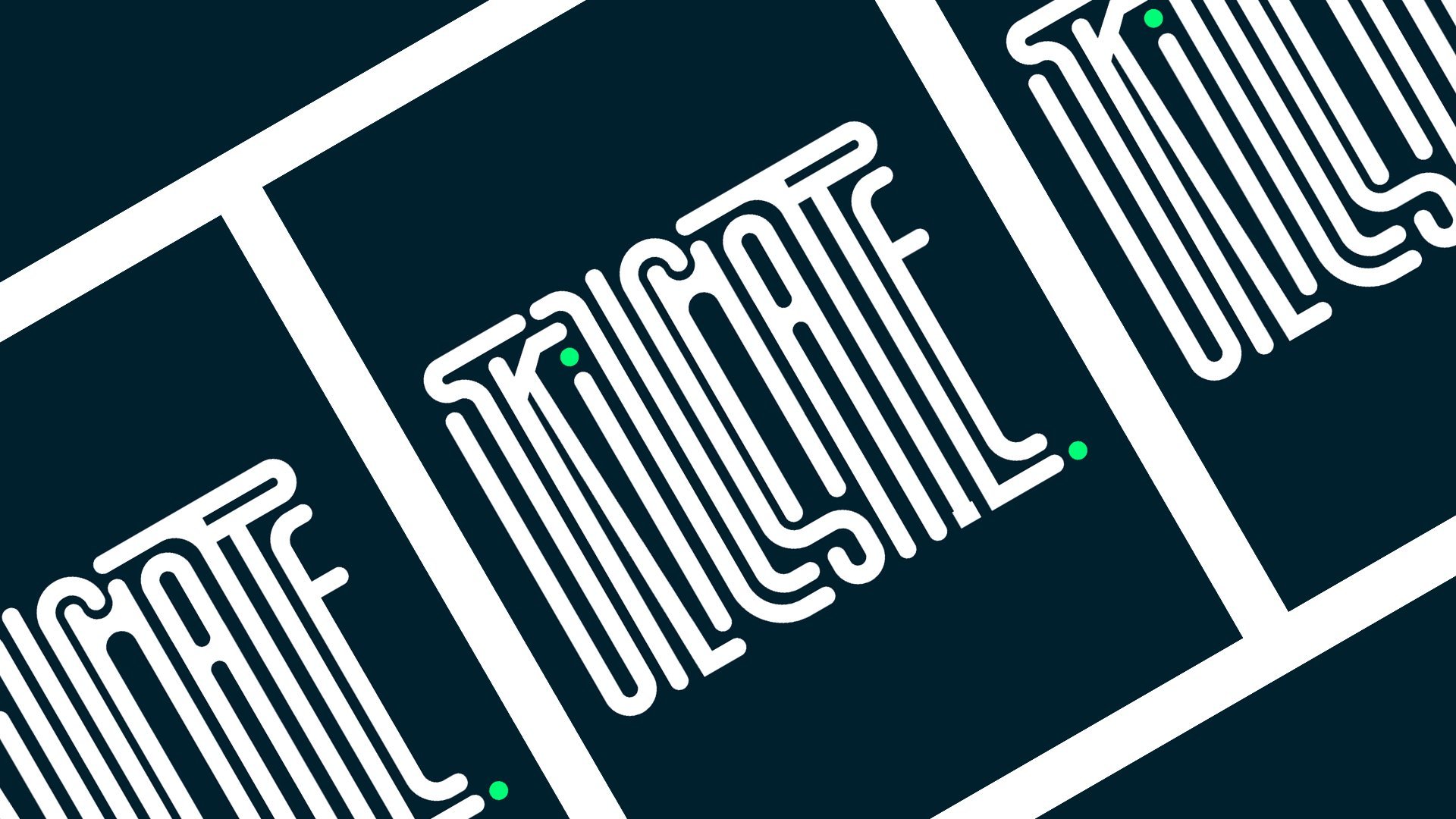
Classe de typographie expérimentale | Marcos Silva | Skillshare
Classe de typographie expérimentale
Leçon 01 Personnalisation de type Partie 01
Leçon 02 Personnalisation de type Partie 02
Leçon 03 Personnalisation de type Partie 03
Leçon 04 Déformateurs de personnalisation de type
Leçon 05 Personnalisation de type Effets 3D
Leçon 06 Ajouter de la couleur à notre type personnalisé
À propos de ce cours
L'expérience de typographie est l'une des choses les plus amusantes et les plus difficiles à faire dans le design. J'adore le processus de création de quelque chose que je peux penser, c'est cool ! Et je peux aussi le lire !
Cette classe s'est inspirée d'un moment où j'ai juste décidé de pousser certains vecteurs autour d'une police de caractères et j'ai fini par faire dire que mon collège de mon côté est vraiment cool. Vous devriez faire plus ! Donc j'ai fait plus et j'ai fait un cours à ce sujet !
Dans ce cours, je vous guiderai à l'intérieur des outils d'illustrateurs adobe bien que vous soyez libre de choisir le chemin que vous voulez si votre résultat est différent du mien c'est ok !
Cette Clas est une expérience, il n'y a pas de client, pas de date limite, personne ne dit que vous ne pouvez pas le faire ou que vous ne pouvez pas en typographie.
Ensemble, nous allons changer de police de caractère, nous allons déformer une police de caractère, la mettre à l'échelle et l'étirer, nous ferons tout ce que nous ressentons.
Je vous assure que vous aurez quelque chose à montrer à votre mère et peut-être qu'elle l'aimera ou non ! Peut-être qu'elle va penser, ce que j'ai fait ? Peu importe que ce soit que nous avons fait quelque chose aujourd'hui !
Ce cours est adapté à n'importe quel niveau de compétence, il est facile à suivre, donc vous n'avez pas besoin de vous soucier de ne pas avoir beaucoup d'expérience dans Illustrator.
Je suis fini ! Alors faisons le maintenant ?
1. Bande-annonce: typographie est autour de nous partout où nous allons et regardons, est la communication. C' est l'interaction, c'est la personnalité et l'expression. Ça fait partie de notre existence. Bien qu'il se sent plus que cela est également matière première que vous pouvez utiliser comme base pour construire et créer des dommages. Cette classe est sur le fait de faire ça. Il s'agit de rendre Type plus expérimental, plus unique et plus personnel. Il s'agit d'obtenir une police de caractères et de la transformer, déformer, de la déplacer, de la mettre à l'échelle de haut en bas. Il s'agit de créer quelque chose de nouveau et d'intéressant avec le matériel qui existe déjà. Bonjour, je m'appelle Michael Silver, designer et animateur, et bienvenue dans mon nouveau verre de typographie expérimentale. Dans cette classe vous guidera dans mon processus créatif et expérimental au sein d'Adobe Illustrator. Nous allons faire la police de caractères et tout changer à ce sujet. Ensuite, nous explorerons les couleurs, les distorsions de distorsion, les effets 3D et les textures. Mais le plus important, nous aurons beaucoup de plaisir à le faire. À la fin de la classe, vous aurez un type personnalisé conçu totalement unique à vous et à votre personnalité, prêt à ajouter à votre portfolio et à partager sur vos pages de médias sociaux. Rejoignez-moi pour créer quelque chose de nouveau aujourd'hui. Alors commençons. 2. Personnalisation de type 01 - Partie 01: Donc, nous sommes un nouveau hétéroclite. Et la première chose que nous allons devoir faire est bien sûr de créer un nouveau tableau d'art. Donc, nous allons d'abord créer un nouveau fichier. Créons de nouveaux, et utilisons dix cents, dix cents pixels. En fait, vous n'avez pas besoin de vous inquiéter pour cette résolution parce que c'est le début. Nous allons juste essayer quelques expériences comme jouer avec le type et frapper réellement exporter notre projet final, que nous exporterons plus tard. Et plus tard, nous pouvons nous inquiéter de la résolution que nous allons utiliser remplissage. Donnons simplement un nom à cette expérience de topographie 01. Appuyez sur Créer, et allons-y. Donc, la première chose est que vous devez en fait, vous pouvez réellement utiliser n'importe quel téléphone pour faire cet exercice. J' ai en fait trouvé ce type dans le site, le font.com, et j'aime vraiment l'utiliser pour ce genre de choses parce que c'est comme une police serif. Et nous ne pouvons pas pousser un peu ces serifs et jouer avec eux, mais vous pouvez en fait utiliser n'importe quelle police de votre choix. Donc, pour cet exercice, j'ai utilisé le nom Skillshare comme plate-forme. Nous allons juste sélectionner cette Skillshare linéaire et juste aller Maintenant, vous pouvez être centré est aligné au centre pour l'instant. Pas de marais Cleveland et prends mon téléphone. Quadro, audacieux. C. Comme vous pouvez le voir, c'est comme non, comme ces équipes de baseball en Amérique, ils ont ce genre de téléphones gras comme vraiment épais. Et nous aimerions sérieux, nous aimerions vraiment de beaux détails. Ce n'est pas comme s'ils étaient à la limite de quoi que ce soit. Je pense juste qu'ils ont le goût d'un très bon début pour quelque chose de même génial. Alors c'est tout. Vous pouvez, mais encore une fois, vous pouvez réellement utiliser n'importe quelle police. Tu veux ? Je pense que celui-ci est en fait plus facile, sont en fait, nous allons le laisser sur les téléchargements pour le fichier dans les téléchargements de fichiers. Donc vous pouvez les gars, donc vous pouvez tous l'obtenir et utilise une police est que j'utilise et peut en fait être plus facile. Et puis vous pouvez simplement expérimenter avec d'autres types de polices, cette même technique. Donc, la première chose que nous devons faire en fait est de sélectionner cette police ici. Et passons à Object and Expand. Allons frapper OK. Ce que cela fait, c'est qu'il élargit notre type. Donc, ce n'est plus modifiable et vous ne pouvez pas le changer. Si vous voulez le modifier, vous pouvez simplement aller à éditer et annuler, développer, puis vous pouvez réellement revenir en arrière et changer le nom si vous le souhaitez. Mais si vous êtes d'accord avec le mot que vous choisissez, c'est bon ? Allons nous agrandir à nouveau. Appuyez sur OK. Et nous allons juste zoomer. Donc, la première chose que vous devez faire est de comprendre comment, comment vous voulez réellement déformer cela. Sur ce cas, je vais juste tirer ça comme je vais commencer par la première lettre S ici. Et je vais utiliser cette touche fléchée ici, l'outil de sélection directe. Vous pouvez simplement aller sur une barre d'outils ici ou simplement appuyer sur a ou v, qui va réellement choisir entre celui-ci. Celui-ci est un outil de sélection qui déplace votre sélection. Il n'édite pas réellement nos nouveaux points moins nombreux. Et celui-ci ici, le blanc, peut réellement sélectionner des points spécifiques et les déplacer. Revenons donc à celui-ci, à la sélection directe, une grande sélection. Et je peux sélectionner les points ou moins comme ça. Donc, comme vous pouvez le voir, tous ces points au-dessus de cette ligne ici sont en cours de sélection. Et je vais les sortir comme ça. Donc nous comme juste un début, c'est déjà à l'air vraiment agréable. Je pense que la police aide beaucoup, bien sûr, parce que c'est comme si c'était un tel héritage. Cette police demande en fait d'être modifiée ou jouée avec. Donc Anchiornis continuent à pousser certains éléments comme ici et jouer avec ça. En fait, expérimentez autant que vous le pouvez. Peut-être que je vais le faire ici. Et si vous n'êtes pas satisfait de ça maintenant, on pourra le changer plus tard. Il n'y a pas ce n'est pas comme si tu étais coincé avec ça pour toujours. Et je vais le pousser un peu vers le bas. Donc il y a quelque chose qui se passe avec ce k ici. Je pense que je vais juste tirer ce point ici pour trouver, peut-être que j'aurai mes guides ici. Je vais voir les règles et montrer les règles. Et je vais tirer un guide du côté. Si vous sélectionnez simplement le guide ici, vous voyez cette ligne pointillée. Et vous pouvez simplement tirer le guide et déplacer simplement le zoom avant en appuyant sur C et simplement sur Z pour zoomer arrière. Juste pour que nous puissions aligner ce point que nous avons passé à la même ligne, points F, juste comme ça. Donc la prochaine chose est juste de continuer à pousser ce K un peu vers le bas. Et je vais continuer à jouer avec les serifs ici. C' est pourquoi j'aime vraiment utiliser cette police pour cet exercice. Ces serifs sont en fait fonctionne si bien et ils en fait si facile à éditer. Mais encore une fois, vous pouvez réellement utiliser n'importe quelle police. Et faites comme ça. Peut-être qu'on les gardera. J' aime ça. En fait, je vais tirer ces haut, le haut de la lettre I Morales ici. Parce que ce que je veux faire plus tard, Il est également ajouter de nouveaux éléments à cela. Vous pouvez donc modifier votre police de caractères. Et, et avait en fait quelques détails à elle. Et je vais tirer, peut-être que je vais pousser encore un peu plus. Alors je peux tirer un peu plus la lettre S, juste comme ça. Et peut-être que je vais le faire. Alors je peux étendre la jambe du k sous cela. Et continuant à créer ce genre de puzzle que vous avez tort, comme travailler, désolé, je ne pouvais pas me souvenir du nom en anglais. Et vous obtenez les lettres impliquées les unes avec les autres en créant ce genre de compositions presque complexes que la Russie devra prêter une certaine attention pour réellement comprendre et lire. Et c'est ce que je trouve vraiment intéressant. C' est comme quand vous en fait, il n'y a pas, il y a quelque chose là-bas. Eh bien, en fait, vous devez faire attention et le lire du tout, comprendre ce qui se passe là-bas. J' y arriverai rapidement plus tard. Et peut-être que je vais changer cette lettre L aussi. En fait, j'ai oublié de faire quelque chose qui est que je dois dégrouper cette lettre. Sinon EBIT, si je le déplace, je peux déplacer des individuels si j'en ai besoin. Donc, juste pour sélectionner en utilisant notre outil de sélection ici. Et je vais à Object and Ungroup. Parfait. Et maintenant, nous allons éditer ma lettre L. Je vais la tirer vers le haut. Et ça va pousser ça un peu comme ça. Et nous allons MOOC oh, deuxième moi de retour. Ainsi, ils peuvent tourner les uns avec les autres plus ou moins comme ça. Et en tirant. Encore une fois, l'idée ici est de créer comme, comme la composition plus agréable que vous pouvez. Peut-être qu'en fait il suffit de tirer ça. C' est le réel dépendra du type que vous utilisez. Donc je suis vraiment curieux de savoir quel mot avez-vous entré que nous utilisons pour cet exercice ? Parce que c'est un monde différent. Nous avons en fait une composition différente. Et c'est là qu'il le ferait, ce qui le rend si intéressant et si unique. C' est comme si un, si les gens utilisent le même mot, ils auront une approche différente de cet exercice. Et nous serons vraiment intéressés de voir comment vous utilisez réellement les contrats du même mot d'une manière différente. Et je ne sais pas si tu sais ce que je veux dire. Comme si c'était parce que c'était très personnel et que tu avais ton type de personnalité à elle. Peut-être que je vais le faire comme ça. Et puis on poussera ce H ici. Je vais, encore une fois en utilisant l'outil de sélection ici, je vais tirer cela vers le bas. Je suis désolé, j'utilise probablement toujours le raccourci, ce qui est une envie. Parfois, je ne vais pas à la barre d'outils et j'appuie juste sur un et je continue juste. Je suis désolé si cela vous dérange, mais vous pouvez en fait utiliser aussi bien, ce qui est un très, vraiment sympa un raccourci clavier pour l'utiliser. Et vous en fait simple petit peu de temps. Je n'entends pas tout le temps là-bas. Choisissons simplement ceci. Et je suis quand j'ai besoin de sélectionner deux points différents. Mais je peux le faire en une seule fois. J' utilise réellement le maintien, la touche Maj comme ceci et je les sélectionne. Donc, le clip sélectionné, puis je déplace cela vers le bas. Voyons voir. Quand je déplace celui-ci aussi ici. Nous allons pousser un autre guide ici pour nous assurer que le H correspond réellement au k là. Vous n'avez pas besoin de réellement vous pouvez libérer comme vous le souhaitez, n'avez pas besoin d'utiliser les grades Kaiser. C' est, c'est expérimental, alors soyez libre de ne pas suivre n'importe quel type de règles et juste s'amuser. Et je suis, je fais ça pendant un moment. En fait, j'aime parfois qu'il garde une sorte d'ordre parce que ces compétitions sont si complexes d'une certaine façon. Je vais juste garder, donc parfois je vais juste zoomer avant et arrière pour que je puisse vraiment voir plus ou moins comment, comment ça va couvrir ? Comme, je pense que si vous faites un zoom arrière, ça peut avoir une meilleure idée de ce qui se passe. Et quand vous zoomez, vous savez si bien ce qui se passe dans la composition ? C' est pour ça que je fais toujours ça. Je suis désolé. Et déplaçons juste la lettre a ici. Donc, comme nous avons le H là-bas, je pense en fait pousser cette page un peu comme ça. Déplacez notre serif du ciel ici et poussez celui-ci vers le bas. Peut-être l'aligner. Encore une fois. Tu n'as pas besoin de voir, supposons que tu t'amuses. Et si vous travaillez avec des notes InDesign, je travaille à temps plein. Parfois, ça devient si traditionnel. Vous pouvez faire beaucoup avec les polices de caractères parce que Donald, ils proviennent d'un client ou de leur police de marque. Et vous êtes un peu limité ce que nous pouvons faire avec eux. Vous devez respecter les règles, donc je ne veux pas créer de règles ici. Je veux juste que tu t'amuses et que tu crées quelque chose de nouveau. Alors faisons ça. Ici. Juste comme ça, peut-être que je vais pousser ça vers le bas. Essayez de gérer ça. Oui, parfait. Comme peut-être que j'essaierai à nouveau demain. Parfois, je éteins mes guides que vous pouvez simplement aller ici à nouveau et juste montrer guide. Donc s'ils ont disparu dans votre écran, je vais juste à Delta. Maintenez à nouveau la touche Maj pour sélectionner plusieurs points. Et juste faire super. Et bien, continuons. Je pense que nous avons tendance à penser que je suis vraiment content de cette sélection. Nous sommes juste maintenant, nous avons le, notre, nos cendres est en fait assez difficile parce que la façon Iz conception réelle, parce qu'il est juste besoin d'un coin supérieur ici. En fait, je dois faire quelque chose comme ça pour ne pas perdre la forme du R et devenir quelque chose d'autre que vous pouvez réellement le comprendre. Pour être très prudent avec celui-ci. Selon un téléphone que vous avez choisi de faire cet exercice où il n'a pas vraiment d'importance parce que peut-être votre r n'est pas aussi bloqué que celui-ci. Et ceux-ci, vous pouvez probablement faire ce que vous voulez. Ne perdez pas les informations qui sont parfaites. Désolé, parfois je prends ces pauses pour boire de l'eau. Et j'ajoute le contraire, quand je l'expliquais avant juste par notre sœur, je sais que faire ça est des cours de Skillshare et je suis tout à fait connu sur l'enregistrement moi-même expliquant quelque chose. Donc, à chaque fois que je fais un cours, j'ai vraiment développé cet ensemble fou. Et je commence à avaler et à respirer très profondément pendant que je suis en train d'enregistrer et je pense que c'est tellement ennuyeux, mais je ne sais pas si ça va être fini, mais je vais continuer parce que j'ai beaucoup aimé ça pour arrêter. Et d'accord. Donc, comme vous le voyez déjà, je pense qu'on pourrait jouer un peu plus. Qu' est-ce que la lettre E gauche ? Maintenant, tu vas juste tirer ça comme ça. Oui. Et oui, je pense qu'on a déjà une très belle composition qui se passe ici. On dirait une empreinte numérique, comme une empreinte digitale. Et réel, réel comme il voulait vraiment faire quelque chose ici sur le, J'index quelque chose de plus proche de la, à la police de caractères. Donc, donc chacun a en fait un peu d'influence comme une étiquette de couleur graffiti sur elle. Je ne sais pas comment. Je commence juste quand j'ai commencé à faire ce genre de travail. Nous tapons des visages. Moi, je viens de commencer à modifier certaines phrases temporelles parce qu'en ce moment, je travaillais dans une agence et le travail que je faisais n'était pas, elles sont très créatives. Et je veux juste ouvrir Illustrator et commencer à jouer avec des polices et finir par faire cet effet vraiment cool. Et j'ai continué à le faire pendant un moment. Parfois, nous avons besoin de s'ennuyer pour créer quelque chose de cool. Je pense que l'ennui est comme nous, nous ne respectons pas vraiment. Je pense que l'ennui est aussi important. Continuez à bouger cette chose, essayant de faire des formes différentes. Et vous pouvez en fait continuer cela pendant des siècles, pendant des heures si vous le voulez. est important, c'est que nous sommes sûrs que vous essayez réellement de déplacer des choses et de créer différents types de compositions. Et voyez lequel. Peut-être bouger l'œil, l'a ici. Peut-être que je vais choisir ces points ici. Et je vais le faire descendre. Oui. C'est un peu différent. Peut-être la même ligne que le H ici. Tout comme oui. Eh bien, je pense que nous avons notre première expérience. La première chose est comme, comme vous pouvez le voir, est juste de jouer avec la forme et de la modifier autant que vous le souhaitez. Toi. C'est illimité. n'y a aucun moyen que j'aime le résultat Hendra. Tu es en fait, tu peux y aller. J' étais comme je l'ai dit, on peut juste continuer à le faire et le modifier. Ensuite, je crée un nouveau div, nouvelles formes et je déplace les curseurs autour. Peut-être, bonsoir. Peut-être qu'on va pousser ça. Donc c'est vraiment dur d'arrêter. En fait, si vous, parce que vous obtenez ainsi dedans et essentiellement si divertissant, presque comme juste continuer à modifier ces formes, ces lettres, et créer de nouvelles formes. Ce type de loyer de terrain que nous pourrions réellement mettre quelque chose ici au milieu et poster comme collaborer en ligne et dire, essayer d'entrer dans le point de terminaison ou autre chose, il suffit de supprimer cela. C' est là que j'aime commencer. Je voudrais commencer par quelque chose comme rapide et réellement basique, mais quelque chose de rapide et différent. Et à partir d'ici, le C sera notre première expérience. Distorsion et maintien de la base de la forme continue immobile de la lettre. Désolé. Ensuite, je voudrais modifier encore plus loin d'ici. 3. Leçon 02 de personnalisation - Partie 02: Donc, pour que nous ne perdions pas ce design ici, je vais juste sélectionner l'outil Plan de travail ici sur le coin. Et je vais déplacer ce plan de travail vers la gauche. Et sauvage, je suis sauvage pressant Alt. Je vais juste le tenir et le faire glisser sur le côté. Juste comme ça. Donc tu compliques mon plan de travail. Et ça garde mon design là. Et nous gardons ces plans de travail ici juste pour la sécurité. Et donc si vous avez vraiment besoin de retourner ici, on peut facilement copier ailleurs. Donc celle-là nous, nous avons conçu en premier, c'est très dur bord. n'y a pas de coins très mous ici. Et terminer chaque article est cool. Si vous êtes satisfait de cela, vous pouvez juste arrêter tout de suite et juste aller à la prochaine, la prochaine des formulaires. Et il suffit d'expérimenter avec les couleurs et la 3D. Mais si vous voulez vraiment explorer un peu plus, il y a autre chose que vous pouvez faire sur cette police. Donc, en fait, j'aime aussi continuer à éditer cela. Peut-être que je vais juste nettoyer quelques bords comme ici parce qu'on n'utilise pas celui-là. Donc, quatre qui sont en cours, juste, vous pouvez simplement peut-être supprimer les points de votre outil de stylet et utiliser l'outil Supprimer le point d'ancrage et nettoyer les points comme ceci. Et peut-être porter un guide du coin à nouveau. Et juste moins Tony propres Guides, Show Guides. Et puis aligner les guides comme ça. Ou vous pouvez vraiment l'utiliser et juste en trouver un dont nous n'avons pas besoin. Tout comme celui-ci ici, où vous pouvez réellement utiliser l'outil de forme, l'outil de rectangle ici. Et c'est sur un rectangle comme ça, correspond parfaitement au coin que vous voulez supprimer et il suffit de sélectionner votre lettre et votre rectangle et d'aller trouver Pathfinder ici. Utilisez simplement ce mode différent, le modèle Minus Front, qui supprimera l'objet qui se trouve devant la lettre. Nous ne ferons pas cela par étape. Donc, certaines mères en auront besoin, un autre avis que nous voulons donc pas bon, pas de souci beaucoup en ce moment. Mais je pense que je voulais faire sur ces lettres pour qu'on fasse ces virages. La façon dont vous voulez le faire est d'utiliser notre outil de sélection. Je vais sélectionner ces deux coins ici. Et je vais pousser ces petits points blancs ici comme ça jusqu'à ce qu'ils fassent un coin rond parfait. Et je vais continuer à faire ça ici. Et sur celui-là. Comme ça. Donc, de cette façon, nous créons un différent que différents troubles comme il est plus arrondi et plus doux et commander un avant. Faisons-le juste. Joli. K lettre aussi. Choisissons cet arc. Peut-être commencer par 1 d'abord et essayer de faire une belle courbe. Et supprimons simplement ces points ici parce que nous n'en avons pas besoin. Et essayez juste de faire la meilleure courbe qu'on puisse entendre. Parfois, ceux-ci sont difficiles parce que vous devez garder la même largeur entre les deux et parfois pas si facile à utiliser. Oui, quelque chose comme ça. Parfait. Donc je vais aller au sommet ici. Je vais tirer ça vers le bas. Celle-ci aussi. En fait, peut-être que je vais commencer par celui-là parce que nous ne voulons pas tuples qui choisissent peut-être ces deux points, celui-ci et celui-ci. Et fais ça. Alors. Et puis on le fait peut-être ici. Et celui-là. Poussez ces deux points ensemble comme ça, et peut-être que celui-ci n'aura pas vraiment. C' est juste parfois assez difficile à faire en fait. Oui, il suffit de le sélectionner à nouveau. Peut-être que je peux juste le faire à la main jusqu'à ce que ça soit beau. Parce qu'on peut faire une forme parfaite comme ça, juste essayer de le faire. Donc, il garde la même largeur ici. Oui. Parfait. Allons éteindre nos guides. Je vais juste voir des guides. Guides pour le moment. Et merci celui-là comme ce coin Rhonda du K. Peut-être voyons si nous pouvons vraiment savoir. Fais juste ce coin. Peut-être, peut-être que je vais juste tirer, continuer à éditer le cygne ici. Donc c'est en fait la ligne droite ici. Et peut-être en fait va tirer ce terme en sélectionnant ici. Et je vais pousser ce K. Je dois partir un peu plus loin. Et peut-être que je vais supprimer ceci ici. Modifiez depuis le début de ma phrase de type. Vous voyez, nous avons déjà défini à partir d'ici parce que ce qui est, parfois ce qui fonctionne sur cette tuile. Ils le feront, ils travailleront vraiment beaucoup sur celui-ci. Et vous continuez à vous améliorer et à vous adapter comme vous le souhaitez. Allons juste tirer ça, faire mal, va toujours le faire rond. Les gars vont avoir cette partie supérieure. Juste comme ça. Et celui-ci en fait, je vais supprimer ces coins en utilisant l'outil de suppression ici. Et supprimez simplement. Je vais utiliser un guide pour m'aider à aligner ces points là. 00 cartes. Donc oui, à la même chose, ce point ici. Je vais supprimer ces points parce que quand je fais réellement la courbure, ces points arrêteront ma carrière là-bas. Et je ferai de même. En bas. Sélectionné. Supprimer les points d'ancrage. Juste comme peut-être que je vais juste cliquer sur celui-là droit. Et puis je vais juste tirer ça en utilisant notre code. Je vais supprimer celui-là. Parfait. Paul est plus court, tout est beau quand je zoom arrière. Faisons tourner nos guides de guides. Il a l'air très beau tableau. Et peut-être que je vais juste sélectionner ceci et le tirer vers le haut. Je vais supprimer celui-là. Can, je vais essayer de le faire suivre la même chose. On en a un carré. Et je vais me tromper. Donc, je correspond vraiment. Et ensuite, nous vous demanderons ce coin ici. Voici la recherche vraiment heureux avec ces résultats déjà. Continuons à pousser. Cela peut être, je vais continuer à éditer ce k. juste quelque chose comme ça. Bricoleur. Nous allons supprimer ces points ainsi sur le L. Allons obtenir toutes les spécifications gentils ici, montrer sortes. Et supprimez simplement ce point. Guide ici. Supprimer ce point est tout à fait un exercice sans fin parce que c'est comme bouquet. Comme je l'ai déjà dit, vous pouvez simplement continuer et continuer à expérimenter que la stabilité style Follies est comme chaque fois que vous modifiez quelque chose que vous obtenez un nouveau IT, et puis vous avez juste une autre idée. Et puis. Vous avez vraiment besoin de vous contrôler, donc ça s'arrêtera même si vous, sinon vous allez être là dedans. On va finir parce que tu vas l'éditer tout le temps. Mais c'est ce qui arrive quand on s'amuse. Vous réparez. Je veux juste continuer à s'amuser et continuer à concevoir des trucs cool. C' est tellement Mode. Vérifie un peu. Oui, en fait, va supprimer celui-ci ici aussi. Je vais chercher un guide ici. Je vais supprimer celui-ci et celui-ci. Poussez ce point vers le bas, faites le mal. Bien sûr, comme il est vraiment difficile d'utiliser ce genre de style dans notre travail quotidien, en fonction de l'industrie pour laquelle vous travaillez. Peut-être qu'elle a travaillé pour Nike ou si vous êtes un designer indépendant ou illustrateur, sera plus facile à appliquer comme ça. Mais je pense que quand je fais réellement ce genre d'exercices créatifs et d'expérience Mike, une certaine façon, je reçois, je développe de nouvelles idées ou compétences que je peux utiliser dans le projet professionnel à mon travail. Ce qui est comme, je ne pourrai jamais modifier notre forme de marque comme ça. Bien que peut-être je peux apprendre quelque chose de la composition et effectivement présenté à mon directeur artistique et peut-être peut nous inspirer à essayer de prendre un peu plus de risques. Mais je n'ai cette procession qu'à cause de petits exercices que je recommande de faire tous les jours. Et c'est vraiment cool parce que comme quand vous faites quelque chose d'expérimental à cela, vous avez en fait la chance de suivre votre voix, suivre vos décisions. Vous savez, pas comme suivre une ligne directrice très spécifique de la marque. n'y a pas de ligne directrice qui avait poumon est d'avoir du plaisir et expérimenter et de partager cela avec le monde et peut-être inspirer quelqu'un. Ou peut-être que vous faites juste une nouvelle affiche pour votre chambre. Tu sais, ce n'est pas comme si je n'avais pas besoin d'attendre quoi que ce soit de ça. Encore une fois, juste s'amuser. C' est pour ça que je fais ce cours pour autant de tests. Tabouret, supprimer est L aussi bien à Marshall vraiment apprécié tant. Et j'ai fait cet exercice plusieurs fois afin que je puisse réellement l'expliquer et essayer de le rendre aussi divertissant que possible. Mais c'est juste comme c'est différent de mes autres tutoriels qui sont plus IE, ils sont plus techniques d'une certaine manière. Et celui-ci est juste, est plus créatif que technique. Et ce qui me donne plus cette occasion d'être réellement dans la conception de ceci et en fait le garder comme ce genre de conversation et d'expliquer quelques morceaux de décisions blanches et pourquoi je fais cela et pourquoi permettre tant d'expérimenter et partager cette vidéo. Peut-être que je vais juste tirer ça un peu ici parce que je pense que cette forme ici est vraiment petite par rapport aux autres. Donc je vais juste pousser ça un peu comme ça ici. Je vais avoir besoin de déplacer ce S va sélectionner ces points parce que lorsque je déplace cette forme de L là-bas, j'ai besoin d'adapter la lettre S aussi bien. Et je vais m'assurer que je fais ce tour aussi. Et maintenant, faisons-le comme ça. Comme ça. Parfait. Oui, j'ai l'air super. Encore une fois, je vais juste supprimer ces points ici parce que en fait ne pas faire beaucoup sera amusant si j'étais en fait, était en quelque sorte mettre le L à l'intérieur. Mais alors j'aurai besoin de peut-être que je peux l'essayer, mais maintenant peut-être que je vais juste partir comme ça. Je vais juste supprimer ces points ici et je vais juste y aller. Parfois, c'est parfois facile. Gardez votre vie simple pour le temps et je ne veux pas que vous partiez de votre journée pour expliquer ça. Donc je montre ce processus. Je vais juste pousser ça ici. Donc, ces guides m'aident beaucoup. À la fin de, comme tous les côtés actifs, je finis avec des médiums de guides. Et si tu bouges ton cœur, pour une raison quelconque, tu en fait, Yochai n'a plus de sens. Et il est si dur, parfois je fais ça. Et je vais juste sélectionner ces points ici. Et celui-là. Je vais juste pousser comme ça, comme ça. Comme si vous essayez de les aligner plus ou moins pour réellement vous aider à garder la même largeur de trait. Et nous ferons la même chose ici. Ce sera encore dur parce qu'on n'a pas beaucoup d'espace pour qu'elle bouge. Est donc peut-être que je vais essayer de changer cela un peu. Laisser S est en fait difficile aussi. Comme nous l'avons vu ici, est à cause de cela, en fait ce contraste de différentes formes. Peut-être que si je pouvais juste avoir plus d'espace là-bas. Je vais pouvoir, euh, vraiment intéressant comment nous envers vous, vous avez décidé d'utiliser un oeil et s'il vous plaît assurez-vous de partager ça parce que ce sera tellement amusant. En fait, deux personnes décident d'utiliser les mêmes mots et ils ont des approches différentes et des concepteurs différents. Je pense que c'est là que la magie se produit. Essayons de tirer ça de la même façon que l'autre. Oui. Et peut en libérer un. Je suppose que c'est juste comme ça. Vous avez juste besoin d'être sûr que vous ne perdez pas réellement la forme. Il ne devient pas comme si ça cessait de perdre été s et commence à devenir comme quelque chose d'autre. Cela n'a aucun sens pour vous. Vous devez encore être capable de lire. C' est ça. Même prend le relais est plus difficile à lire, mais vous devez toujours être en mesure de le lire. Sinon, cela perd un peu le sens et nous donne plus, plus d' illustrations pour votre, pour la personne qui lit ou voit cela sur votre fil de médias sociaux. Je vais juste tirer ça. Juste comme ça. Peut-être encore une fois, mon Latinx est juste, juste envie de faire ce look vraiment cool et expérimenter avec les positions des lettres durement. Profitez de cela beaucoup moins de poitrine. Peut-être pousser ça. Le sol est mieux centré. Ils vont supprimer certains points là. Faites ces points, y a-t-il quelques points puis il a été supprimé ici. Je vais mal à ça. On devrait guider l'halocline ici. Si vous Mike Guides, Show Guides. Et supprimez simplement celui-ci, poussez celui-ci aussi. Laisse-moi voir si je peux essayer de faire un coin lisse. Sans être très dramatique ici. Peut-être pas. Peut-être que je vais juste sauter ce bord de la partie là-bas. Et je continue dans le a. maintenant. Je vais pousser ça. Vraiment gentil, j'aime vraiment ça. Et faisons la même chose. Vous pouvez en fait, vous n'avez pas besoin de faire tous les coins arrondis. Tu peux si tu veux. Mais parfois, il est agréable d'avoir une sorte de contraste entre les formes douces sont des puces. Je ne sais pas pour ça. En fait, je vais penser que je veux laisser celui-ci sur le dessus comme un arc, comme un magasin d'intérêt. Et je vais juste éteindre les guides pour l'instant. Et je vais continuer à supprimer quelques points ici. Donc, il est point qui est point décrit son point. Et poussez ça, poussez celui-ci ici. Encore une fois, tant que vous ne perdez pas le sens de la lettre. Juste pour tout le monde, assurez-vous que vous n'allez pas trop fou au point qu'il y a plus de briquets. Et il est comme un graphique très abstrait. Certaines sortes de Skillshare. Et continuez à pousser. Peut-être que je vais faire ce logiciel de coins aussi bien. Peut-être qu'on va pousser ça vers le bas. Ces deux points, les deux points ici. C, aussi longtemps, encore une fois, ce R est très difficile. Et j'essaie de ne pas le gâcher parce que c'est vraiment facile de ne rien devenir. Je vais juste voir si ça marche bien. Si vous en fait, vous devez imaginer si vous lisez ces lettres un par un, cela ressemble-t-il à un S pour vous ? Oui, il le fait. Tellement cool. C' est fait. Et si vous faites le même exercice pour chaque lettre, supprimez-nous celle-ci ici. On dirait qu'il suffit de sélectionner ceux-ci. D' accord ? D'accord. D' accord. Vous m'appelez aller amino. On dirait qu'un K CISC fait une certaine façon est assez difficile à voir. Mais on appellerait le texte pour vous en fait peut comprendre, c'est bon. Et il y a le L ici. Changons peut-être de couleur pour qu'il soit plus facile de comprendre à quoi il ressemble maintenant. Oui. Parfait. Vous avez juste besoin d'être comme vous avez juste besoin d'être sûr. Il est juste pas juste de ne pas partir trop fou, Issachar, si vous voulez toujours trop fou en fait, juste ceci est qu'il n'y a pas de client évoluer, ils juste la créativité et je ne veux pas arrêter tout type de création et unicité dans votre vie. Alors faisons ça, courez ces coins. Je peux en quelque sorte déplacer ceux-ci ici qui juste aligner à nouveau. Assurez-vous qu'il s'aligne. Peut-être que je vais pousser ces allumettes. Outil de pièce de monnaie. Je ne connais pas les guides. Supprimez ces points ici. Poussez quelques guides. Parfois, un cerf-volant est verrouillé et vous devez réellement les déverrouiller si vous voulez, comme, imaginez que vous voulez déplacer ce chariot ici. Elle est enfermée, donc je ne peux rien faire. Donc, pour cela, vous avez juste besoin d'aller aux guides et déverrouiller les guides. Et maintenant vous êtes libre de les déplacer, ce qui vous rend la vie beaucoup plus facile. Et Tilly a dit quelques points de plus. Pour une raison quelconque, il ne supprime pas mon pointeur. Ok, eh bien, allons juste glisser ma lunette ici. Et sélectionnez ces points. Si vous utilisez ces points de coin , ils veulent rester pour une raison quelconque. Personne n'arrive. Laissons-le là pour l'instant. Je vais faire la même chose pour créer une nouvelle ligne ici. Je peux amener mes gars à mes enfants ? Parce que les enfants sont déverrouillés. Quand j'ai essayé de faire un petit point, pense en fait que je fais quelque chose aux guides. Donc je vais verrouiller mon guide. Oui. Était-ce si oui. Si vous avez tous les gars déverrouillés, vous en fait si quand vous vous approchez d'eux, vous pensez, voulez-vous modifier le guide ou ajouter des points au guide pour une raison quelconque ? Essayons juste ça un peu comme ça. Oui. Regardons juste un zoom arrière. Peut faire une comparaison. J' aime vraiment le style et celui-ci aussi. Je ne pense pas qu'il y a le stylet meilleur que celui-ci ? Pas d'adjectifs juste différents. Ils viennent du même endroit qui est déjà fait topographie et c'est une magie que vous venez de porter quelque chose qui a été fait pour quelqu'un d'autre et de créer votre propre chose. C' est comme cuisiner. J' en quelque sorte, il a juste les bons ingrédients. Vous les assemblez, vous les déplacez ici, vous les tranchez, vous je ne sais pas, vous les déchiquetez. Vous les mettez sur une soupe et vous la mangez pour une raison quelconque. Maintenant, pour une raison quelconque, vous les mangez parce que vous avez besoin de manger. Je suis désolé. Parfois, quand je fais cet enregistrement à cet outil avant que je ne suis pas aussi expérimenté encore. Et puis je commence à devenir nerveuse pour une raison quelconque et je commence juste à parler. Et si vous ne mentez pas, si vous préférez réellement les majors, été silencieux tout le temps, ce qui agit expliquant étape par étape. S' il vous plaît laissez-moi cela sur les commentaires. Parce que les divulgations devraient être plus sur l'apprentissage de nouvelles compétences ou pas comme des épingles frapper sur mes blagues. Je suis désolé. Et tirez ça comme ça. Oui, parfait. Et faites la même chose pour le R ici. Bien. Tirez les guides. Mes cartes, Show Guides. Et supprimez le point. Celle-là. Peut-être que tu vas ajouter un ici. Donc, vous correspondez à la même position que le R. et exécutez ce sont des coins comme ça. Continuez à affiner et à trouver des moyens, peut-être que les élites voient les formes en ont besoin ici. Comme ça. E, Désolé, parfois j'utilise le spectacle. Les guides sont juste Commande ou Contrôle sur Windows et coma. Donc, vous pouvez juste changer au lieu d'aller ici et aller Afficher les guides. Ici, il a gardé le raccourci en fait. Vous pouvez simplement utiliser le même raccourci pour afficher et masquer ces guides. Donc, c'est pourquoi parfois ils apparaissent et ne vont pas au menu. C' est juste parce que j'utilise le code de raccourci vrais guides. J' ai appris à être obsédé par apprendre chaque raccourci pour chaque logiciel que j'utilise. Parce que je suppose vraiment obsédé par optimiser mon temps autant que je peux parce qu'ils sont rapides. Je fais quelque chose comme un couple. Le festival soit libre de faire autre chose. Sinon, ce n'est pas comme si je n'appréciais pas le travail que je fais. J' aime le mot hydro, mais parfois vous en fait, plus, plus vite vous pouvez réellement travailler demain, vous pouvez faire, et plus vous pouvez expérimenter avec de nouvelles choses et sur votre projet, j'aurai en fait plus options. Donc, c'est le moment dans les années que je viens d'apprendre à avoir essayé de connaître tous les raccourcis de logiciel d'erreur que j'utilise pour cela. Je pense que vous venez d'entrer dans ce juste en économisant quelques secondes. Mais si vous additionnez ces secondes en N du jour, ou même plus, si vous additionnez les secondes que vous enregistrez à l'aide de vos touches de raccourci. Jusqu' à la fin de l'année. Si seulement quelques heures là-bas. Ma copine m'ennuie vraiment à cause de ça, parce que parfois on travaillait ensemble sur la même table. Nous avons comme une table partagée car nous travaillons de chez nous maintenant à cause du verrouillage et les autres bureaux sont fermés. Parfois, j'essaie de lui expliquer quelque chose et ensuite je dis juste le raccourci pour faire quelque chose qu'elle a besoin de faire. Et elle dit, non, je ne veux pas connaître la touche de raccourci. n'est pas comme ça que je travaille et c'est un choix personnel bien sûr, comme certaines personnes préfèrent utiliser un menu. Donc c'est comme un, c'est comme un système est plus ou moins qu'ils savent où se trouve le personnel au lieu de s'appuyer sur des raccourcis qui peuvent changer avec le temps. Mais parce que je suis tellement obsédé par eux, parfois je ne sais même pas où est l'option sur le menu. Et il finit par être comme, en fait, je ne sais pas où, comment faire ça sans être avec le raccourci, parce que je suis probablement juste utiliser le raccourci pour les cinq dernières années. Et je ne sais pas encore où vous ce qu'il est plus dans le menu. Donc, avec comme tout le monde, j'apprends le codage sur un menu et je trouve mon chemin ici. Et puis sur un menu, je vais juste essayer de voir s'il y a un raccourci pour quelque chose comme quand vous passez par votre menu ici et vous pouvez réellement voir Fs Shift, F7, marchandise pour 11 Royaume-Uni regardent comme essayer de se souvenir de cela à chaque fois. Je pourrais donc être plus efficace dans mon travail quotidien. Donc je pense que c'est ça, C'est la deuxième personnalisation, appelons de cette façon. Et j'aime vraiment ça. Je ne sais pas si je les aime tous les deux. Ils sont vraiment tous les deux entièrement intéressants. Je pense que cette situation de pointe de l'art crée plus comme un sentiment d'élaboration. Et celui-ci crée plus d'un sentiment d'être comme un marqueur. Tu sais, comme si tu essayais juste d'esquisser une topographie dans ton carnet de croquis et que tu essayes de les faire vraiment condenser. Et donc Médicis est la façon dont vous pouvez réellement voir, comme comment vous pouvez personnaliser le même design et continuer à personnaliser jusqu'à ce que réellement développer quelque chose de nouveau. Et nous avons commencé à partir de la police que je vous ai montrée avant. En fait, ça va faire du tableau d'art ici. Donc, vous pouvez réellement comparer cela. Je vais écrire ça à nouveau, Skillshare. Donc je pense qu'il est important de dire que nous, nous avons commencé ici, nous allons, nous sommes allés ici, et maintenant nous sommes là. Et cela, encore une fois est juste comme une recette. Vous obtenez juste vos ingrédients correctement. Vous pouvez essayer avec un téléphone différent et simplement créer des choses différentes. Et juste, continuons à bouger ces trucs. 4. Leçon 03 sur la personnalisation de types - Partie 03: Et maintenant, en utilisant les mêmes conceptions que nous avons déjà créées, modifions en fait encore plus de décharge. Pour ça. Nous allons simplement créer un nouveau plan de travail. Utilisons la configuration de notre plan de travail ici et l'utilisation de notre outil de plan de travail ici. Tenons sans défense comme traîner et déposer six ici. Et faites la même chose pour celle-là. Juste comme ça. Parfait. Donc elle voit déjà personnalisé. Mais maintenant, nous pouvons faire quelque chose comme plus ou moins simplement en utilisant notre outil de sélection ici. Ooh, et peut-être continuer à pousser ça juste un peu comme ça. Tu sais, tu es en train de créer une autre situation pour cette phrase type, qu'il fait un peu moins froid. Et en fait déplacer tat aussi bien. Donc, nous allons juste sélectionner est de maintenir les quarts de sorte que vous pouvez réellement vous connecter. Vous pouvez réellement le faire comme plus sûr parce que si vous, si vous voulez, sans maintenir le décalage, vous n'avez pas beaucoup de précision. Et nous avions décalé ne peut pas juste quitter à travers un beau modèle de précision presque. Et juste tirer cette jambe est à moins que vous puissiez juste dupliquer ça. Et en fait, vous voyez que vous pouvez créer comme un motif vraiment sympa qui est un message secret très Ferris que vous pouvez voir tout de suite. A moins de sélectionner ceci comme cette feuille, celle-ci là. Sauvegardons mon dossier. En fait, je vais à des expériences de typographie de Skillshare. Dites juste des tarifs pour nous, d'accord ? Je ferai la même chose, la même chose pour celle-là. En fait, pour sélectionner un ski et voir jusqu'où je peux aller sans trop bousiller. Comme vous pouvez le voir ici, les zones plus légères en fait vraiment difficile à gérer à cause des courbes. Nous pouvons le faire individuellement. Suggérez, peut-être déplacer le e hors de la base de données pour l'instant. Il suffit de sélectionner cette poussée jusqu'à ce que nous puissions réellement tenir à un arrière là-bas. Quelque chose est arrivé au L ici. Revenons à leur pointeur. Donc, en fait, on ne joue pas avec la cellule. Allons le déplacer. Déplaçons ce Callaway. Il suffit de sélectionner ça comme oh non. Et sélectionnez ça comme Oh, eh bien peut-être qu'on ne peut pas aller aussi loin. Ce qui est bon, revenons ici. Remettez notre E en arrière et voyez une autre, une autre approche et une autre civilisation, il semble quelque chose de différent depuis le début. Et encore une fois, comparons de l'endroit où nous avons commencé à réellement où nous en sommes maintenant. Et c'est encore une fois toutes les possibilités de cadre que vous pouvez juste continuer à faire correct est une sorte de motifs différents avec ces lettres sont des twinkies est un effet vraiment cool en fait. Ouais, je pense que vous pouvez réellement voir combien de potentiel vous avez en utilisant cette technique sur la personnalisation de vos propres téléphones et effectivement obtenir les personnaliser jusqu'à ce que vous réellement notre lourd avec si vous êtes un jack ou vous êtes juste déjà eu assez. Sur la leçon suivante ce que nous voulions réellement explorer certains déformeurs qui sont à l'intérieur d'Illustrator que nous allons former uniformément plus uniforme, discuter de ma forme, donnant comme un peu de profondeur. Nous traitons les outils dans Illustrator. Nous allons utiliser des déformations pour qu'il puisse déformer notre lettre qui court la forme, ou à l'intérieur de l'effet, et nous allons explorer les couleurs aussi. Je te vois dans la leçon suivante. 5. Leçon 04 de déformateurs de personnalisation: Salut et bienvenue à la leçon des déformeurs. J' espère donc que vous êtes heureux avec le déjà réalisé grâce à cet exercice. Et la prochaine chose que nous allons expérimenter, c'est avec les déformateurs d'Illustrator. Encore une fois, Flex son tableau d'art ici. Commençons peut-être par celle-là. J' aime garder mes plans de travail complètement pour que je puisse toujours voir l'évolution du processus d'une manière ou d'une autre. Peut-être que je vais juste aligner celui-ci ici. Celle-là, plus ou moins comme ça. Et celui-ci sera notre couche de déformation. Donc illustré ont un tas de distorsions de travail. De la distorsion des drapeaux à la personnalisation des sources que nous pouvons réellement personnaliser vous-même. Le cristal peut mesurer sur les vecteurs et vous pouvez simplement déplacer des points à l'intérieur de ce maillage. Donc, et c'est ce que nous allons faire. Commençons simplement par sélectionner notre police. Et allons à l'objet et le grouper. Donc, il peut réellement sélectionner n'importe quoi ensemble avant que nous ayons besoin d'eux pour être des lettres individuelles afin que nous puissions réellement les éditer mieux. Mais maintenant, nous sommes satisfaits des résultats, donc nous pouvons simplement aller les regrouper. Alors allons soudainement former ça. Allons à Enveloppe Distort et allons le faire fonctionner. Donc, ce que cela fait est qu'il empêche vos liens Warp, Options, barre de menu. Et ici, vous avez en fait plusieurs types de déformateurs que vous pouvez jouer autour. Commençons par l'arc ici. Et essayons juste d'en faire un 100 pour cent comme ça. Et dès que vous en êtes satisfait, vous appuyez simplement sur OK. Peut-être qu'il va juste mettre à l'échelle ces villes pour que vous correspondiez réellement à notre plan de travail. Vous avez l'air vraiment sympa avec cette composition. Comme si je pouvais encore le lire. Je peux vraiment voir notre K, notre Skillshare est vraiment, vraiment facile à lire en fait et va effectivement avoir avec elle, et c'est vraiment cool. Donc je vais sélectionner cet arc, le premier ici, et je vais, tout en tenant Alt, je vais le faire glisser comme ça. Et je vais appuyer sur la voiture maintenant pour la faire tourner comme ça. Créer ce genre de situation de cercle comme celle-ci. Oui, c'est juste en utilisant notre déformateur. Donc nous pouvons vraiment venir, venir d'ici. Et maintenant on fait ça avec, qui est vraiment comme un 5 tribal de Nouvelle-Zélande. Et allons en faire un autre. Je recommande fortement d'expérimenter. Tous en fait. Il suffit de sélectionner. Est et juste bon de s'assurer de les regrouper. Sinon, si vous ne les regroupez pas, lorsque vous appliquez l'effet, nous appliquerons l'effet en morceaux individuels. Et puis on sera comme, pas très cool. Crois-moi. Allons à Groupe d'objets alors. Objet, Enveloppe Distorser et faire quand vous êtes. À moins que vous ne puissiez changer Ashley à l'arc, vous pouvez changer la façon dont vous vouliez trouver la direction verticale ou horizontale de votre groupe. Juste comme ça, c'est vraiment facile. Ces divers, assez simple, vous pouvez simplement jouer avec cette options de perturbation ainsi. Et passons à un autre, RColorBrewer, qui est vraiment cool parce qu'il crée comme un bord dur sur le dessus et puis arcs en fait le fond, ce qui est vraiment cool. Vous pouvez simplement créer un vraiment agréable, même si vous travaillez sur un logo, il est. Cela fonctionne vraiment très bien. Comme il se sentait travailler pour un logo pour une équipe de football en Amérique ou quelque chose comme ça. Juste comme ça. Faisons juste en créer un nouveau. Et nous allons ensuite à l'expérience suivante ici, à celle-ci aussi. Donc, donc il va sélectionner est en bas ici. Aller au groupe, ça, en fait aller au groupe ici. Donc, la prochaine fois que je dupliquerai, c'est déjà groupé. Et je n'ai pas besoin de refaire ça. Et sélectionnons simplement cet objet et continuons à explorer ceux-ci ici. Peut-être que le drapeau serait sympa. Ou le poisson, j'aime bien celui-là aussi. Vraiment, vraiment cool. J' aime ça. Je pense que vous pouvez voir maintenant la quantité d'options que vous avez déjà. Je pourrais en fait passer les 10 prochaines heures est de vous montrer à quel point ceux-ci sont cool et combien de designs vous pouvez réellement réaliser à partir de ces outils parce qu'il fonctionne si bien est que la typographie personnalisée. Et tout comme rend même tout encore plus intéressant. En fait, presser, lever, se lève comme un drapeau, mais déplace en fait le type plus. Le drapeau contient. La distorsion à l'intérieur de ce cube. Comme ça, ce qui est vraiment cool, mais en fait ne pouvait pas créer des perspectives comme ça. Et le vol le fait aussi bien. C' est comme si c'était tellement potentiel. C' est comme vous pouvez encore, vous pouvez mettre votre, tout votre week-end expérimenter avec cela et faire comme un livre entier de typographie. Juste en utilisant cette typographie personnalisée courbes et et juste continuer à faire différentes destructions va en fait. Faites-en un nouveau parce que je m'amuse beaucoup trop. Je vais mettre ici. Et vous pouvez réellement utiliser comme d'autres types de distorsion, Susan Illustrator, l'efficacité. C' est déjà groupé, je crois, oui. Le leader est-il enseigné dans les yeux pas de groupe là-bas ? Il suffit de sélectionner et de regrouper ensemble. Et vous aurez également ces outils ici, les outils de déformation que vous pouvez réellement utiliser sur ces curseurs ainsi que si vous voulez les modifier en utilisant cette façon, vous pouvez simplement aller ici sur la barre d'outils et simplement utiliser l'outil de déformation ici et juste gâcher autour de lui. Un type comme celui-ci. Les enfants peuvent-ils mieux personnaliser et contrôler les déformations ? Vous pouvez simplement sélectionner l'outil politique. Si vous cliquez deux fois sur un outil, il peut également changer les dimensions du pinceau, mais 500 par 500, donc il est en fait plus grand. Disons juste que c'est, n'est plus lisible. A moins d'essayer de se déformer autant que possible. Parce que c'est intéressant si vous pouvez toujours le lire. Peut-être que je vais rendre ce pinceau un peu plus petit. Et quelqu'un comme ça, je pense que cet outil est le plus recommandé parce que ce n'est pas aussi détaillé, donc vous déplacez simplement les formes un peu autour. Ça ne détruit pas beaucoup comme, je veux dire, comme ça ne crée pas comme des bords vraiment durs. Peut-être l'intrigue 1. Si vous voulez faire un trou sur votre typographie. Et en fait ici, vous pouvez réellement utiliser, si vous utilisez un stylo Wacom, vous pouvez réellement sélectionner ceci. Ils utiliseront un stylo à pression. Donc, au lieu d'utiliser pour la force aperçue de la brosse ici, ici vous utilisez une pression que vous appliquez réellement à leur stylo. Et encore très fort. Mais c'est mieux en fait crée un effet vraiment agréable. Essayons celui-là. Ouais, en fait, ça devrait plaire. Peut-être que je vais essayer de le faire au milieu. Encore une fois. Vous pouvez juste jouer avec celui-ci à votre propre temps. Je voulais juste vous montrer les possibilités de ces outils aussi. Donc, et bien sûr, alors vous pouvez juste mettre à l'échelle cela, déplacer cela encore plus si vous le voulez. Et il suffit d'utiliser les mêmes techniques que celles que nous utilisons dans nos premières leçons. Et continuez à le modifier autant que vous le souhaitez. Je viens de finir celle-là, va juste avoir besoin de vous en montrer un autre, ce qui est qu'on s'est rencontrés. En cas de maillage. Vous pouvez créer comme une distorsion de maillage ici, vous pouvez simplement créer quelques lignes. Alors, nous allons juste nous rencontrer. Utilisez le quatre par quatre pour l'instant. Et vous pouvez réellement bouger, déplacer ces points comme ça, et créer des designs vraiment intéressants aussi. Comme simplement utiliser une topographie personnalisée que vous avez faite à partir d'un autre type. Parce que parfois, si vous voulez commencer votre propre type, je l'ai déjà fait. En fait, il est si difficile. En fait, c'est beaucoup de travail. J' ai fait un projet il y a quelques semaines, et c'était un projet très serré. Et j'ai décidé, pour une raison quelconque, de concevoir. Je vais taper tout mon support, la probabilité pour ce projet et a fini par être ion et un PVC. Mon temps pour finir ça parce que le client ne l'a pas demandé. Le client ne l'a pas fait parce qu'un client ne l'a pas vraiment demandé. Donc j'ai pris ça tout seul et je ne regrette pas parce que j'ai eu beaucoup de plaisir à le faire. Je vais faire quelques problèmes supplémentaires dans la course parce que alors le client voulait des fichiers et l'a réellement demandé la police que j'ai utilisée. Et puis quand j'ai dit sont en fait la police de l'utilisateur final que la conception, c'est amusant. Et je n'ai pas créé le fichier de police pour cela. Et puis il a dit, j'adore la police où nous avons un problème maintenant parce qu' il faut créer de nouveaux atouts et votre travail est terminé. Et donc j'ai juste fini par envoyer à leur concepteur le fichier My Photoshop avec des polices réellement non utilisées là-bas. qui était correct, ils ont fini par l'utiliser et poussé un peu plus de travail pour leur équipe auparavant, mais je pense que ça en valait la peine à la fin. Le client était d'épi et tout le monde était heureux. Donc je pense que c'est la chose la plus importante. 6. Leçon 05 sur les effets 3D: Sur cet exemple, nous allons réellement utiliser explorer quelques morceaux d'arbre. Donc illustrator n'a pas fondamentalement fait, vous pouvez réellement faire beaucoup d'outils distribués dans Adobe Illustrator. Ce n'est pas comme utiliser Cinema 4D parce que c'est une image vectorielle et fixe. Mais vous pouvez en fait faire beaucoup. Donc, pour cela, nous allons simplement regrouper ces polices d'abord. Sinon, il va appliquer l'effet individuellement. Et allons aux effets ici et l'onglet et allons en 3D. Et ici, vous avez trois types de traités différents, trucs que vous pouvez utiliser. Nos perspectives ne sont peut-être pas vraiment vers vous pouvez utiliser. Donc, commençons par, je pense que le seul là à accepter de travailler pour celui-ci est x à la variable n. Parce qu'ils sont en rotation. On fera pivoter la forme des lettres autour d'eux-mêmes. Et leur révolution. Nous faisons tourner les lettres autour d'eux-mêmes. Donc, à la fin, nous ne viendrons pas à comprendre l'édition. C' est là, puis tournez. Ce sera comme l'outil Perspective, plus que tout. C' est juste, je voulais juste te montrer. Dans le cas où vous voulez réellement avoir ce type de frappe comme une perspective isométrique. Il y a la rotation est la meilleure option pour vous à coup sûr. Mais vous n'avez pas la profondeur des lettres. Vous avez juste comme il est encore 2D est en fait aligner très précisément avec des angles comme celui-ci. Et juste, annulons ça. Et passons à 3D, Extrude et Biseau. Donc, nous allons juste commencer à tourner est en fait parce que nos couleurs noir et nous faisons réellement les travaux avec des lumières. Et parce qu'il est noir, les Alliés n'affectent pas beaucoup. Donc, avant d'y aller, vous pouvez simplement annuler cela pour l'instant et changer pour peut-être un gris clair, quelque chose comme ça. Et sélectionnez-le à nouveau. Et passons à 3D et extrude et biseau. Donc maintenant nous pouvons voir plus ou moins ce qui se passe, ce qui est vraiment cool. Nous pouvons réellement tourner est et voir en fait. C' est ce qui se passe ici. Vous pouvez simplement choisir une perspective isométrique. Donc, en fait, je fais beaucoup d'illustrations isométriques à mon travail. Et j'ai appris à aimer ça parce que j'en avais besoin. Et en fait, c'est très intéressant. Il donne comme essayer des sentiments dimensionnels à votre travail d'illustration. Et ce n'est pas très efficace dans le temps, mais c'est vraiment amusant à faire. Vous pouvez juste des perspectives extraordinaires ici. Tous comme des boîtes. Et vous pouvez réellement vous déplacer et faire n'importe quelle perspective que vous voulez réellement. Besoin d'être précis. Vous pouvez suivre ceux-ci ou il peut simplement créer le vôtre. Vous pouvez simplement bouger les angles ici et continuer à faire le tour. Ou en fait quand ils utilisent un isométrique. Par exemple. Et je vais appuyer sur OK. Et le truc est comme, parce que c'est déjà, il a déjà été rendu plus ou moins comme ça. On peut juste changer les couleurs ici. Et nous allons, nous allons plaque d'appels en 3D. Donc, en fait, vous ne le perdez jamais. Vous ne pouvez donc pas modifier les couleurs. Et la seule façon de rendre votre vie un peu plus difficile. C' est comme si vous développez cet objet, si vous allez simplement à l'objet et le développez, con